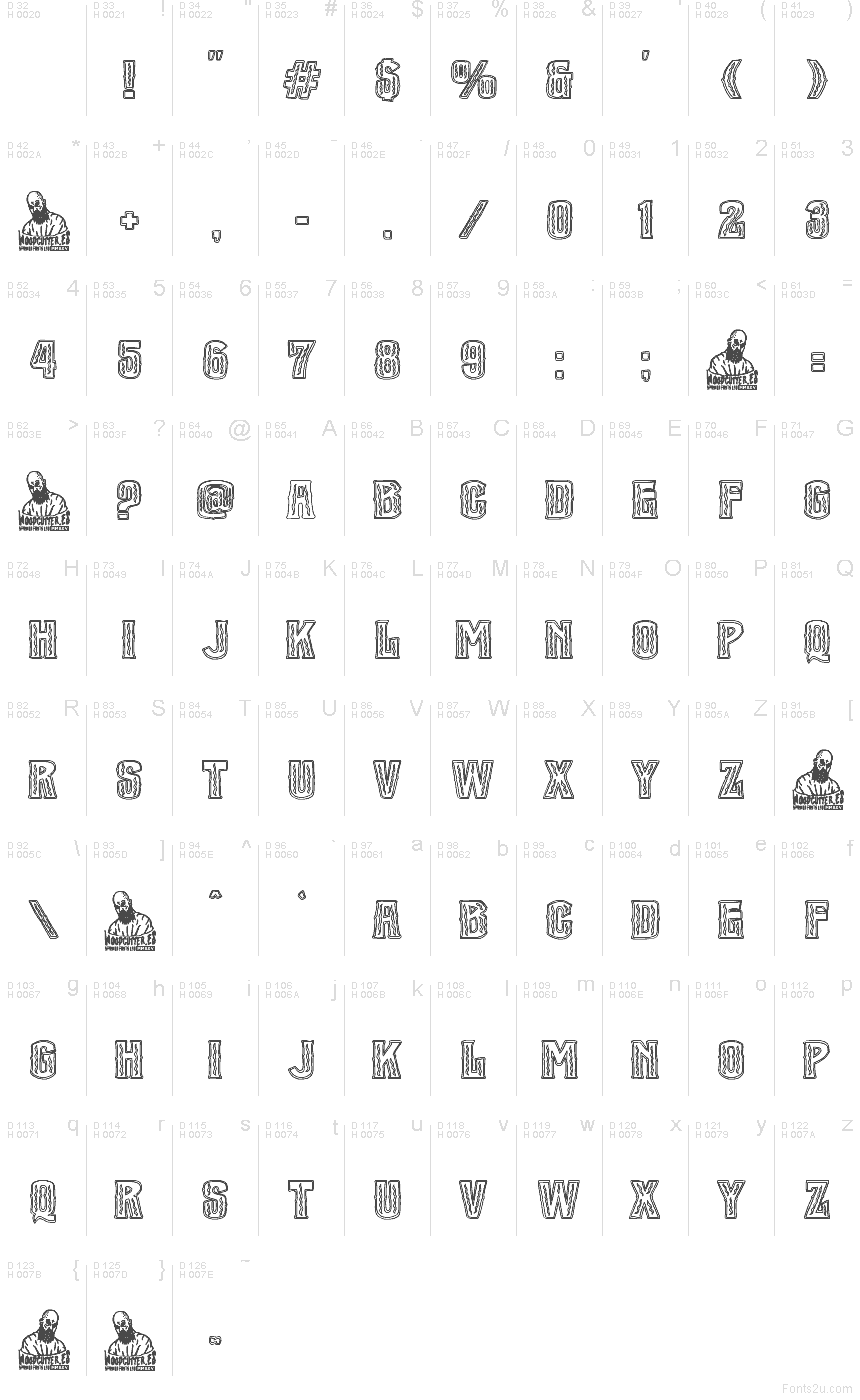
Bourbon Club Outline
Bourbon Club Outline di Woodcutter Manero è un font display western gratuito con lo spirito ruvido e autentico dei vecchi insegne da saloon. Le lettere sono racchiuse in forme squadrate, mentre un secondo contorno interno irregolare e i bordi usurati conferiscono all'intero design un aspetto intagliato e vissuto, che ricorda più i cartelli della frontiera che un poster patinato.
È una scelta naturale per etichette di whisky, branding per bar, locandine di festival, titoli e merchandising dove una parola breve ha bisogno di quel tocco polveroso in stile Americana. Essendo un font gratuito, è perfetto per loghi, testate e grandi iniziali: il trattamento a doppio contorno dona infatti abbastanza presenza anche a poche lettere per caratterizzare l'intera pagina.